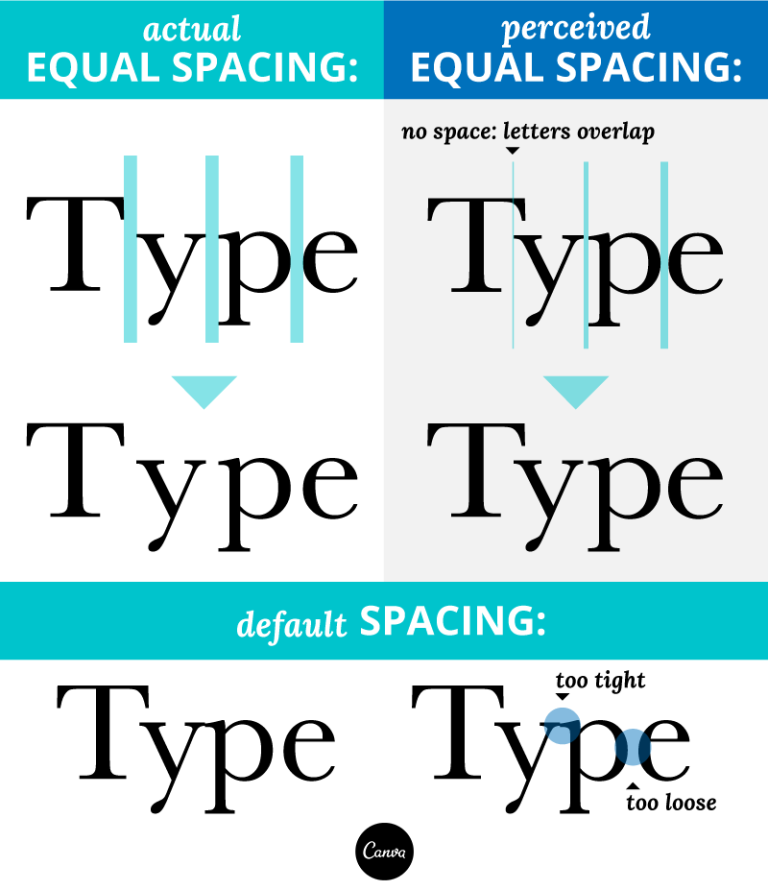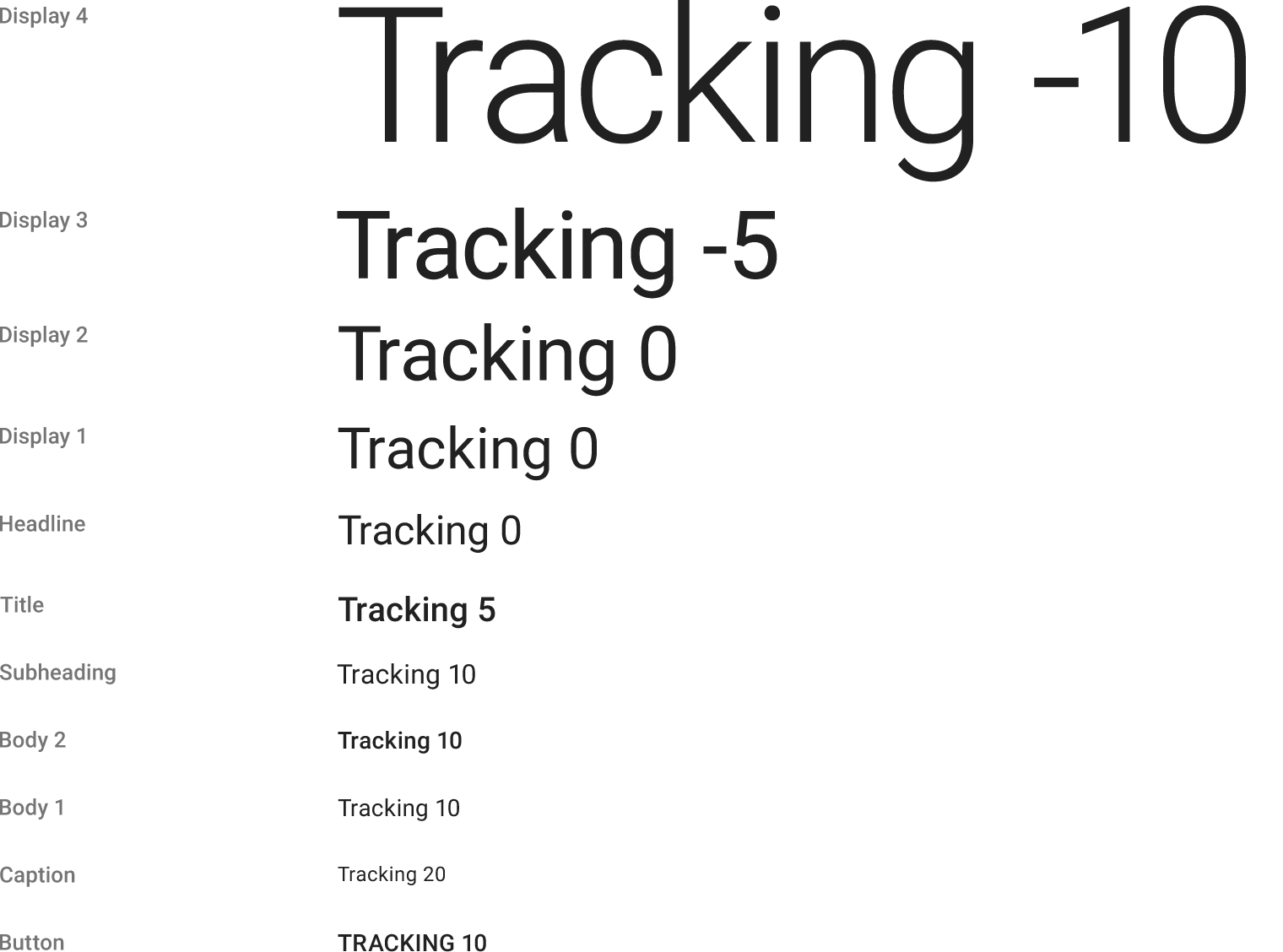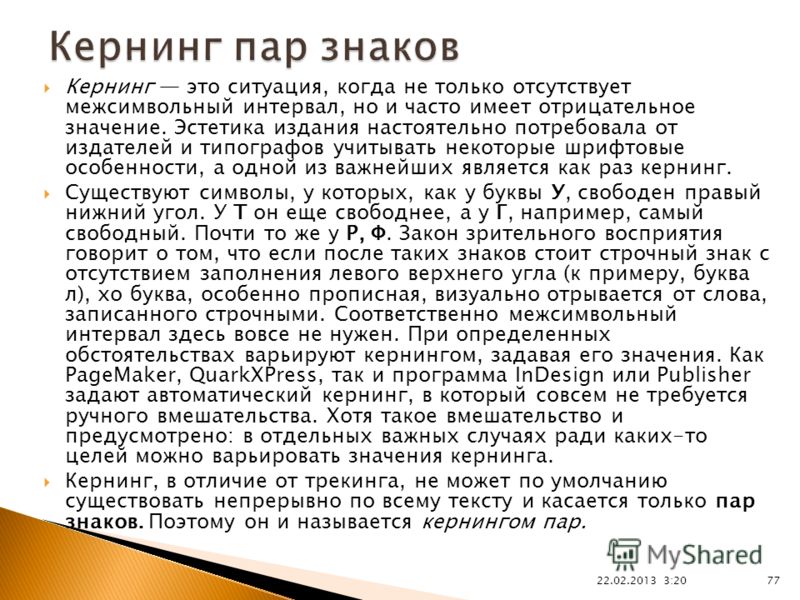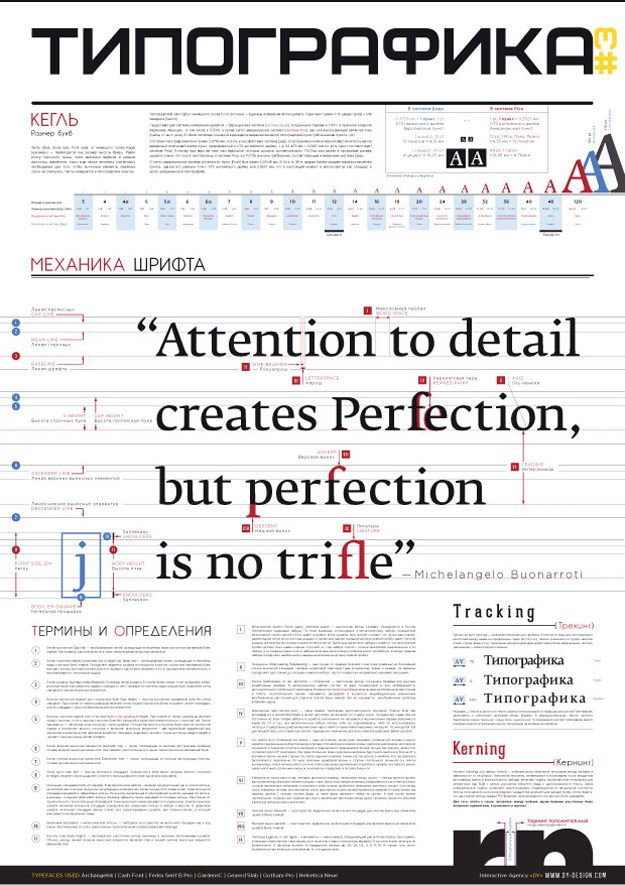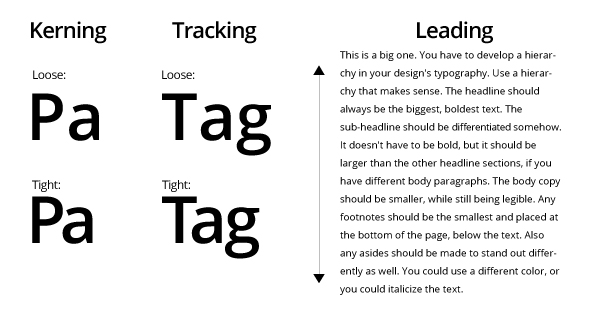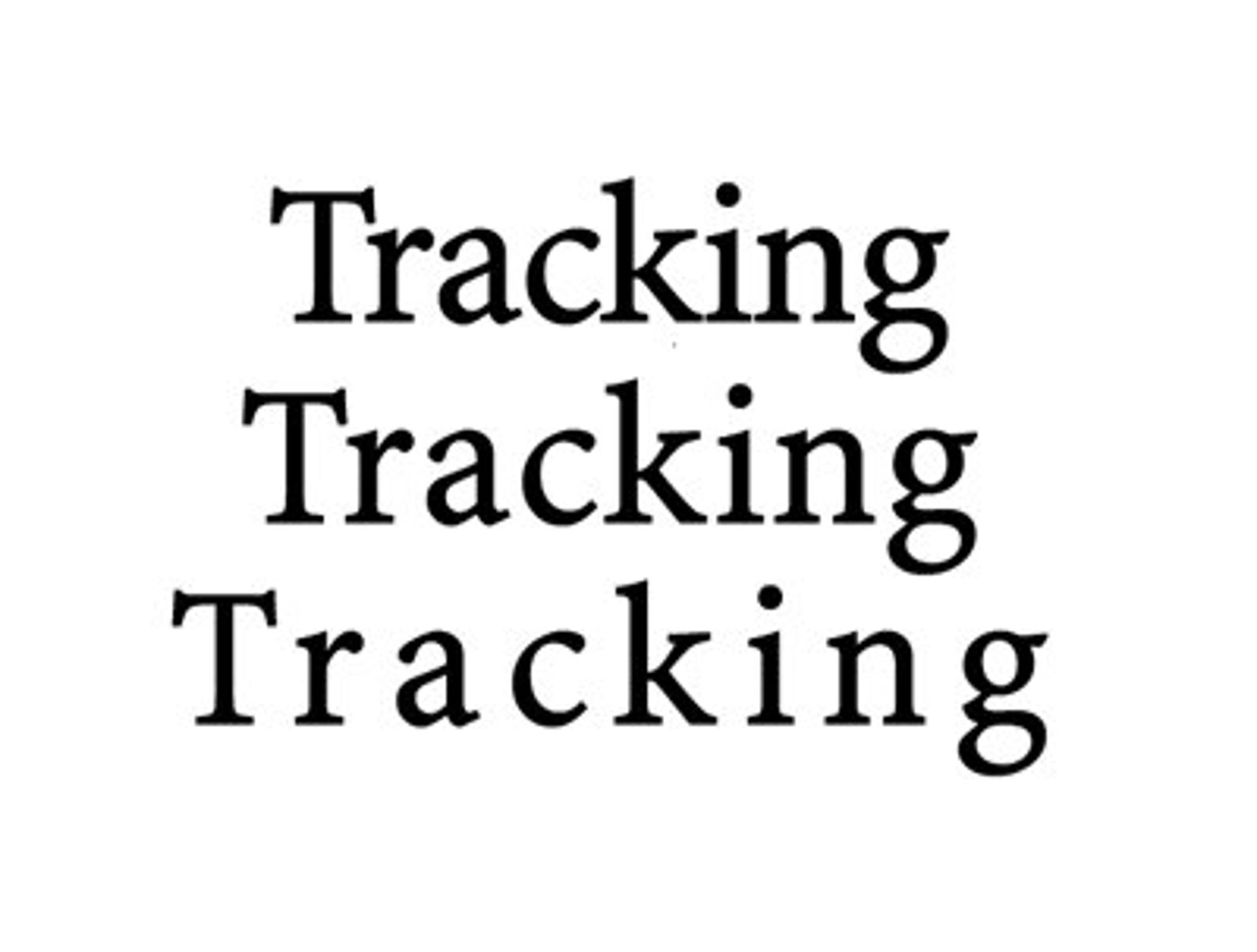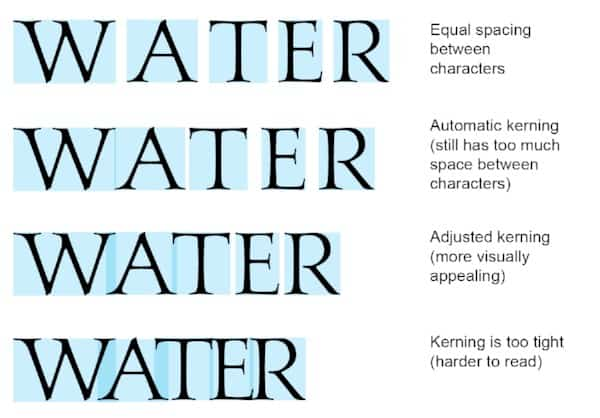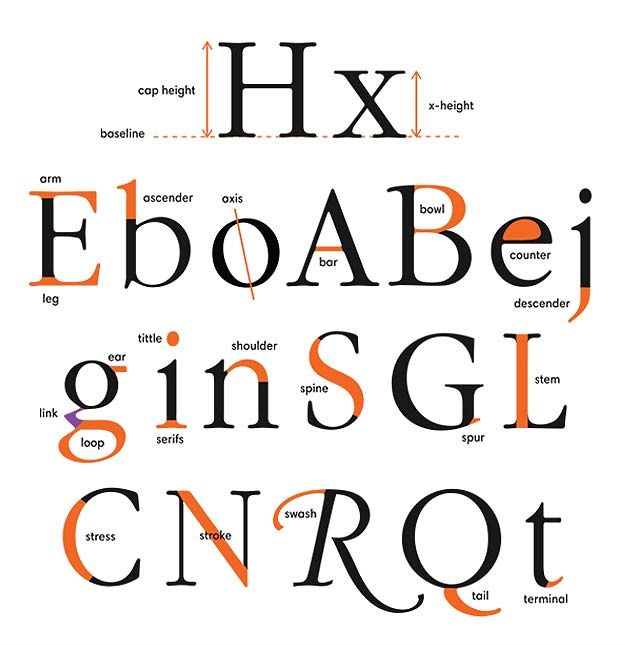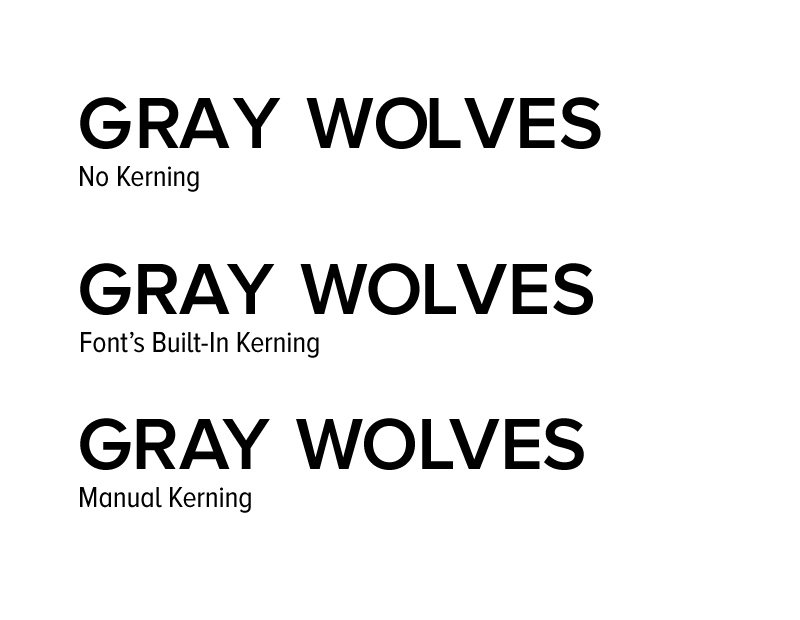
Изменение интервалов в тексте — Служба поддержки Office
Интервалы между знаками можно изменять как для выбранного текста, так и для отдельных знаков. Кроме того, вы можете растянуть или сжать текст целого абзаца для придания ему желаемого вида.
Изменение интервала между знаками
При выборе параметра Разреженный или Уплотненный между всеми буквами устанавливаются одинаковые интервалы. Кернинг регулирует интервалы между отдельными парами букв, уменьшая или увеличивая их.
Равномерное увеличение или уменьшение интервалов между всеми выделенными знаками
Выделите текст, который требуется изменить.
На вкладке Главная нажмите кнопку вызова диалогового окна Шрифт, а затем щелкните вкладку Дополнительно.
Примечание: Если вы используете Word 2007, эта вкладка называется Межзнаковый интервал.
В поле Интервал выберите параметр Разреженный или Уплотненный, а затем введите нужное значение в поле на.
Кернинг знаков, размер которых превышает заданный
Выделите текст, который требуется изменить. -
На вкладке Главная нажмите кнопку вызова диалогового окна Шрифт, а затем щелкните вкладку Дополнительно.
Примечание: Если вы используете Word 2007, эта вкладка называется Межзнаковый интервал.
Установите флажок Кернинг для знаков размером, а затем введите нужный размер в поле пунктов и более.
Изменение масштаба текста по горизонтали
Масштаб текста изменяется путем его сжатия или растяжения.
Выделите текст, который вы хотите сжать или растянуть.
На вкладке Главная нажмите кнопку вызова диалогового окна
Шрифт, а затем щелкните вкладку Дополнительно.Примечание: Если вы используете Word 2007, эта вкладка называется Межзнаковый интервал.
Введите нужное процентное значение в поле Масштаб.
Процентное значение, превышающее 100 процентов, растягивает текст. Процентные значения ниже 100 процентов сжимают текст.
Изменение междустрочных интервалов
Чтобы увеличить или уменьшить интервал по вертикали между строками текста в абзаце, лучше использовать стиль, используемый в абзаце.![]()
Найдите стиль, который вы используете, в коллекции » стили » на вкладке » Главная «.
Щелкните стиль правой кнопкой мыши и выберите пункт Изменить.
В центре диалогового окна вы увидите кнопки междустрочный интервал, позволяющие выбрать одинарный, 1,5 x или двойной интервал. Выберите интервал, который вы хотите применить, и нажмите кнопку ОК.
Если вы хотите применить к стилю определенный междустрочный интервал, нажмите кнопку Формат щелкнитепо стрелке в левом нижнем углу диалогового окна » Изменение стиля » и выберите пункт абзац.
С помощью раскрывающегося списка
Дополнительные сведения об изменении стилей в Word можно найти в статье Настройка стилей в Word.
15 самых употребляемых типографических терминов
Если вы не дизайнер и не верстальщик, то вам пригодится небольшой ликбез по основным типографическим терминам, которые могут означать совсем не то, что вы думали.
Гарнитуру часто путают со шрифтом, но это не одно и то же. Дабы понять разницу между ними, непосвященному в тонкости типографики читателю рекомендуем запомнить простую ассоциацию из детства: гарнитур. В смысле «набор мебели», где ключевое слово — «набор». Гарнитура — это набор группы шрифтов; семья шрифтов с общими стилистическими особенностями.
Классификаций гарнитур множество, самая общая — антиква, гротески, рукописные, акцидентные и тд. Существует великое множество гарнитур, обладающих собственным именем, произошедшим от эпохи создания (Таймс), от имени создателя (Гарамон), национальной принадлежности (Голландер) или какой-то технической особенности (Компакт). Фактически, это фамилия семьи.
Шрифт — набор символов, составляющих единую стилистическую и композиционную систему. Если говорить проще, то разнообразные вариации с высотой, толщиной, наклоном, размером и расстоянием между буквами на тему одной и той же гарнитуры и есть шрифт. Соответственно, группа шрифтов разных видов и размеров, имеющих одинаковое начертание и стиль — это гарнитура.
Кегль — это не какая-то там кегля. Кегль в типографике — это всего лишь размер высоты буквы. От самой высоко выступающей палочки и плечика до самой низко свисающей закорючки и хвостика.
Красивое французское слово «интерлинья́ж» (от фр. interligne), похожее на конфеты «грильяж», переводится дословно как «написанное между строк» и означает расстояние между двумя строками. Обычно принято устанавливать интерлиньяж на 1/5 часть больше кегля — так, при наборе 10-м кеглем интерлиньяж составляет 12 пунктов. В художественных целях интерлиньяж может быть увеличен или уменьшен, но поскольку от него зависит читаемость текста, то небольшой интерлиньяж применяется нечасто — максимум, в заголовках.
Кернинг (англ. kerning) — это интервал между двумя буквами в зависимости от их формы. Например, если в заголовке или логотипе рядом находятся две буквы со сложным характером — с сильно выступающими элементами, образующие слишком большое расстояние между ними, то рационально их немного сблизить, чтобы визуальная плотность была равномерной.
1. Значения кернинга
Чтобы вычислить значения кернинга, подсчитайте количество единиц шрифта, которое необходимо изменить по умолчанию между символами. Положительные значения увеличивают пространство, а отрицательные значения уменьшают пространство.
(источник)Все зависит от шрифта, который вы используете.Не ожидайте, что значение между двумя буквами будет одинаковым при смене шрифта. Требуемая регулировка может немного отличаться.